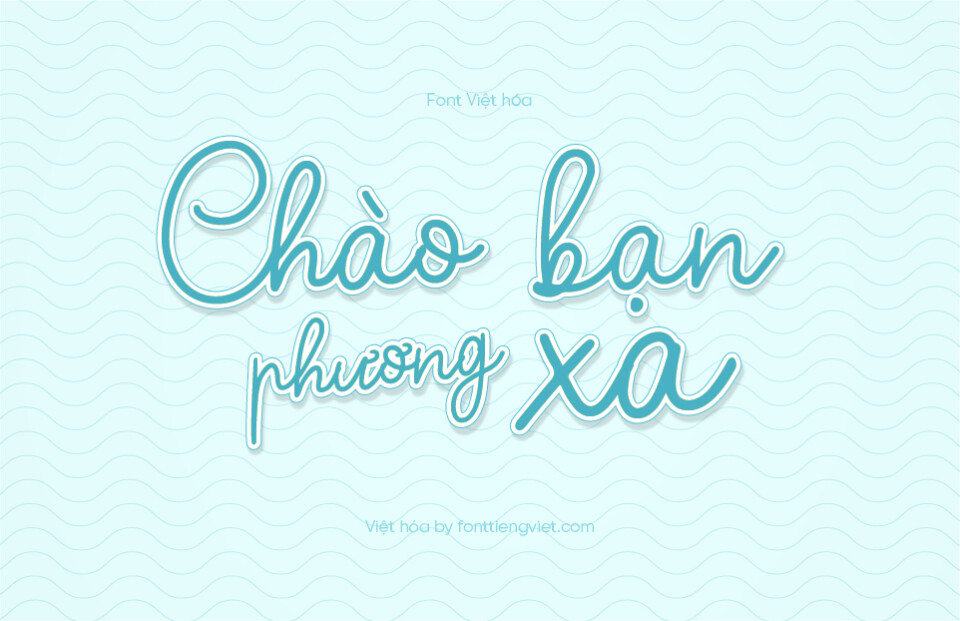
Font Việt hóa 1FTV VIP Pear Leaves
Font Việt hóa 1FTV VIP Pear Leaves: Bộ Font Chữ Nghệ Thuật Đỉnh Cao Cho Thiết Kế
Giới thiệu về Font Việt hóa 1FTV VIP Pear Leaves
Trong thế giới thiết kế đồ họa hiện đại, việc lựa chọn một bộ Font Miễn Phí chất lượng luôn là ưu tiên hàng đầu của các designer. Font Việt hóa 1FTV VIP Pear Leaves nổi lên như một hiện tượng nhờ sự kết hợp hoàn mỹ giữa nét vẽ tay mềm mại và cấu trúc hiện đại. Đây là bộ font được tinh chỉnh kỹ lưỡng về dấu tiếng Việt, giúp người dùng tại Việt Nam dễ dàng ứng dụng vào các dự án truyền thông, giáo dục và trang trí mà không lo lỗi hiển thị. Với phong cách thanh thoát như những chiếc lá lê mùa xuân, bộ font này mang lại cảm giác dễ chịu, gần gũi nhưng không kém phần sang trọng cho mọi tác phẩm nghệ thuật.
Đặc điểm nổi bật của bộ Font Việt hóa 1FTV VIP Pear Leaves
Thiết kế tinh tế và tính ứng dụng cao
Font Việt hóa 1FTV VIP Pear Leaves sở hữu những đường nét uốn lượn tự nhiên, tạo nên một nhịp điệu thị giác rất riêng biệt. Điểm đặc biệt của bộ font này chính là sự cân bằng giữa độ dày và độ thanh của nét chữ, giúp văn bản trở nên dễ đọc ngay cả ở kích thước nhỏ. Các nhà thiết kế thường sử dụng nó cho các tiêu đề sách, thiệp mời đám cưới, hoặc các ấn phẩm quảng cáo cho ngành làm đẹp và thời trang. Sự linh hoạt này giúp font chữ đáp ứng được nhu cầu khắt khe của cả học sinh, sinh viên lẫn những chuyên gia thiết kế chuyên nghiệp đang tìm kiếm sự phá cách.
Tối ưu hóa tiếng Việt hoàn hảo
Một trong những rào cản lớn nhất khi sử dụng font quốc tế là lỗi font khi gõ tiếng Việt. Tuy nhiên, với Font Việt hóa 1FTV VIP Pear Leaves, toàn bộ hệ thống dấu câu đã được xử lý chuẩn xác, đảm bảo khoảng cách giữa các ký tự và dấu luôn hài hòa. Điều này cực kỳ quan trọng đối với các bạn học sinh khi làm slide thuyết trình hoặc giáo viên soạn thảo bài giảng điện tử, giúp tài liệu trông chuyên nghiệp và chỉn chu hơn. Bộ font hỗ trợ đầy đủ các bảng mã phổ biến, giúp việc gõ văn bản trên các phần mềm như Photoshop, Illustrator hay thậm chí là Word trở nên mượt mà và nhanh chóng.
Cách sử dụng Font Việt hóa 1FTV VIP Pear Leaves hiệu quả
Kết hợp màu sắc và bố cục
Để phát huy tối đa vẻ đẹp của Font Việt hóa 1FTV VIP Pear Leaves, bạn nên kết hợp với các tông màu pastel nhẹ nhàng hoặc màu xanh lá lấy cảm hứng từ thiên nhiên. Do đặc thù là font chữ có tính trang trí cao, hãy ưu tiên sử dụng nó cho các tiêu đề chính (heading) hoặc các câu trích dẫn (quote) ngắn gọn. Việc đặt font chữ này trên một nền ảnh mờ (blur) hoặc các họa tiết hoa lá sẽ tạo nên một tổng thể vô cùng bắt mắt và đầy tính nghệ thuật, giúp thông điệp của bạn dễ dàng chạm đến cảm xúc của người xem.
Kết luận về giá trị của bộ font